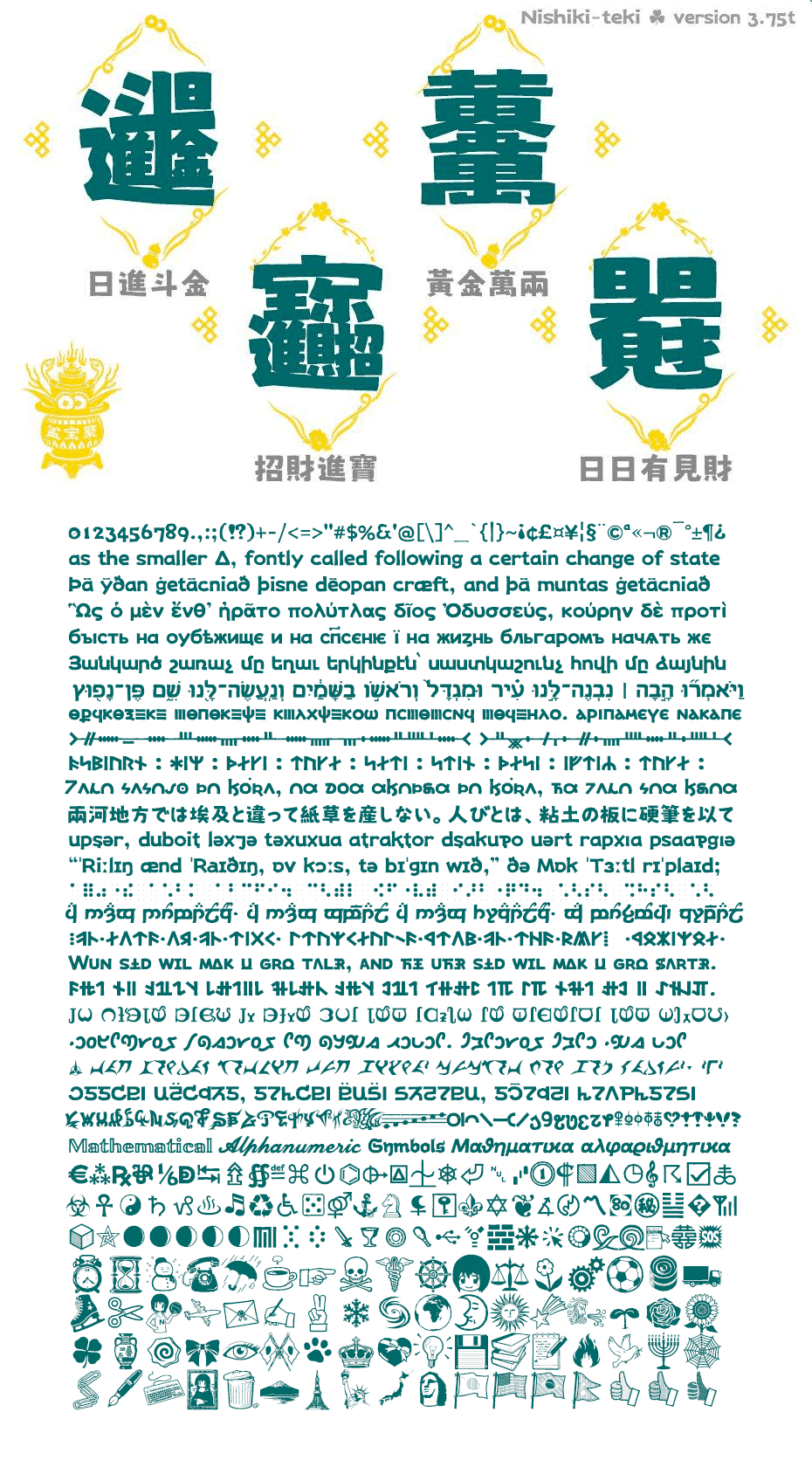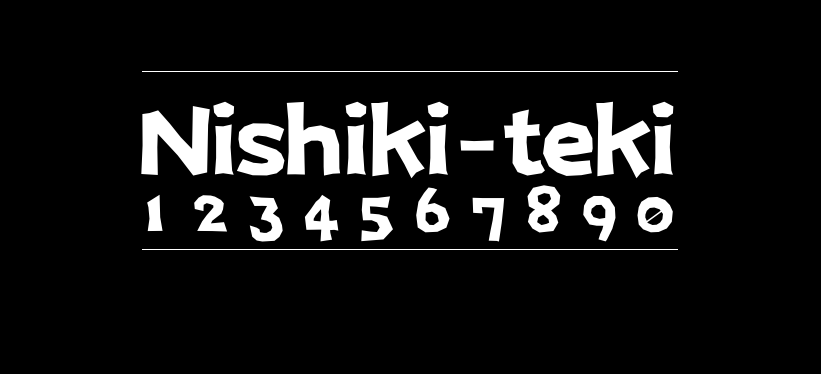
Nishiki-teki
Nishiki-teki是一款可爱的马克笔手绘风格日系免费商用字体。当前版本包括:拉丁语、希腊语、西里尔语、亚美尼亚语、希伯来语、格鲁吉亚语、奥格姆语、北欧古语、科普特语、格拉哥里语,平假名,片假名,注音,汉字,傈僳语,大阪,音标,盲文图案、一定量的表情符号、各种符号和标点符号等。